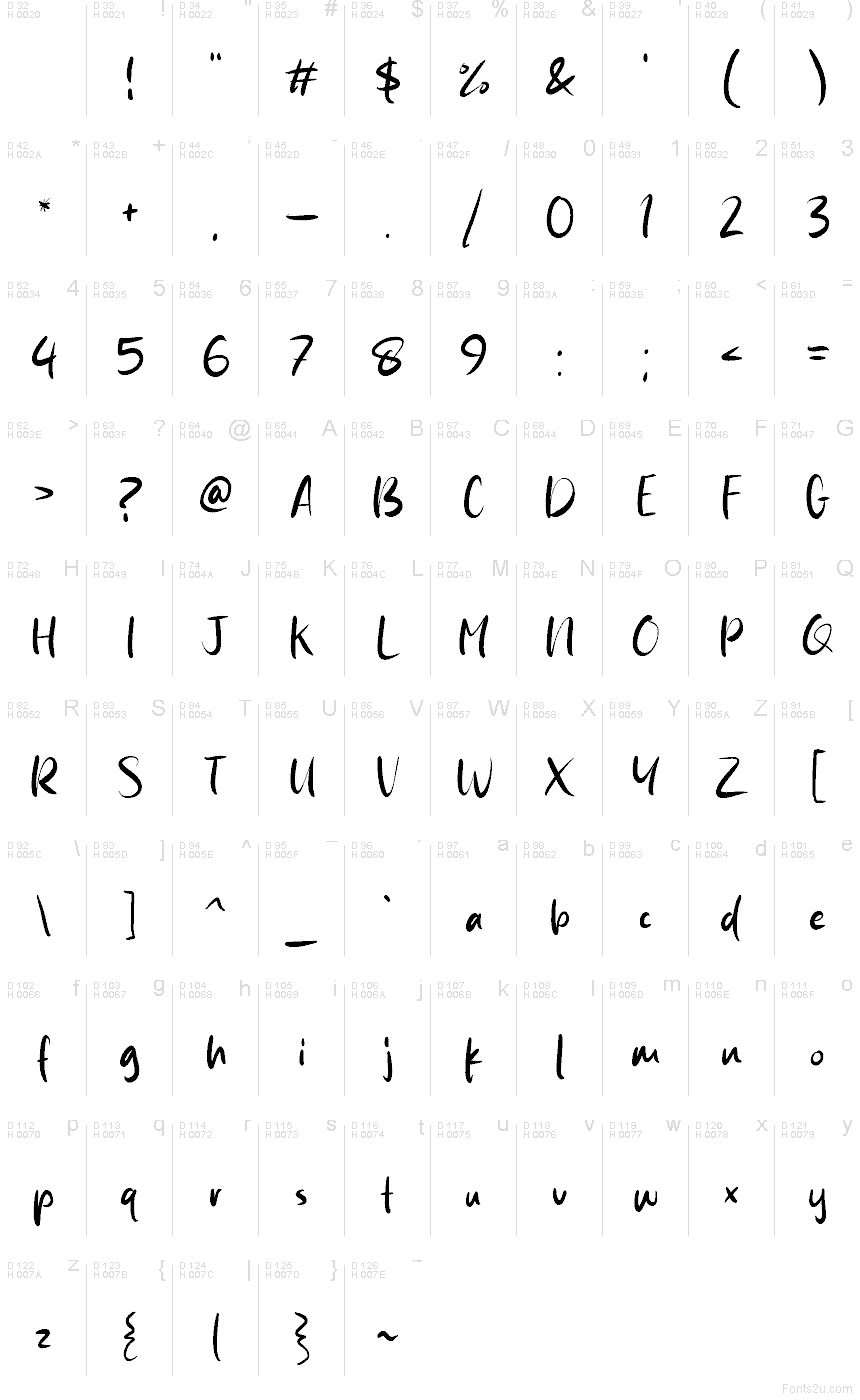
Michael James
Michael James от Origin Type — это бесплатный рукописный шрифт в стиле кисти, передающий легкий и непринужденный ритм надписей, сделанных маркером. Буквы отличаются широкими, насыщенными штрихами и мягкими округлыми формами, что придает им живой, индивидуальный характер, лишенный излишней «причесанности».
Он отлично впишется в постеры, брендинг кафе, обложки альбомов, открытки и посты в соцсетях, где нужно добавить тепла и динамики. Будучи бесплатным шрифтом, он также хорошо работает в заголовках и коротких подписях на упаковках, так как выразительный контраст штрихов и свободный ритм делают даже короткие фразы по-человечески близкими.